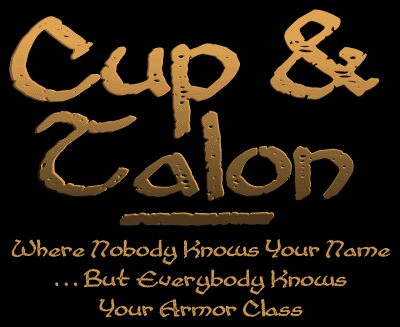
Die Cup and Talon von S. John Ross besitzt den rauen Charme handgezeichneter Buchstaben – mit fleckigen Strichen und unebenen Kanten, die an Tinte auf rauem Papier erinnern. Diese kostenlose Schrift hat einen lockeren, fast kalligrafischen Charakter, der Worten eine wilde, märchenhafte Ausstrahlung verleiht und sie in Überschriften sowie kurzen Phrasen hervorhebt.
Cup and Talon entfaltet seine Wirkung am besten in großen Größen, kombiniert mit einer klaren serifenlosen Schrift für den Fließtext. Diese kostenlose Schrift passt perfekt zu Fantasy- oder Horrortiteln, Tabletop-Spielen, Buchcovern, Postern, Flyern, rustikalen Verpackungen und charakterstarken Logos, bei denen Textur gefragt ist, ohne die Lesbarkeit zu beeinträchtigen.
A mediocre bit of hand-drawn calligraphy made more interesting and useful with expert stressing.